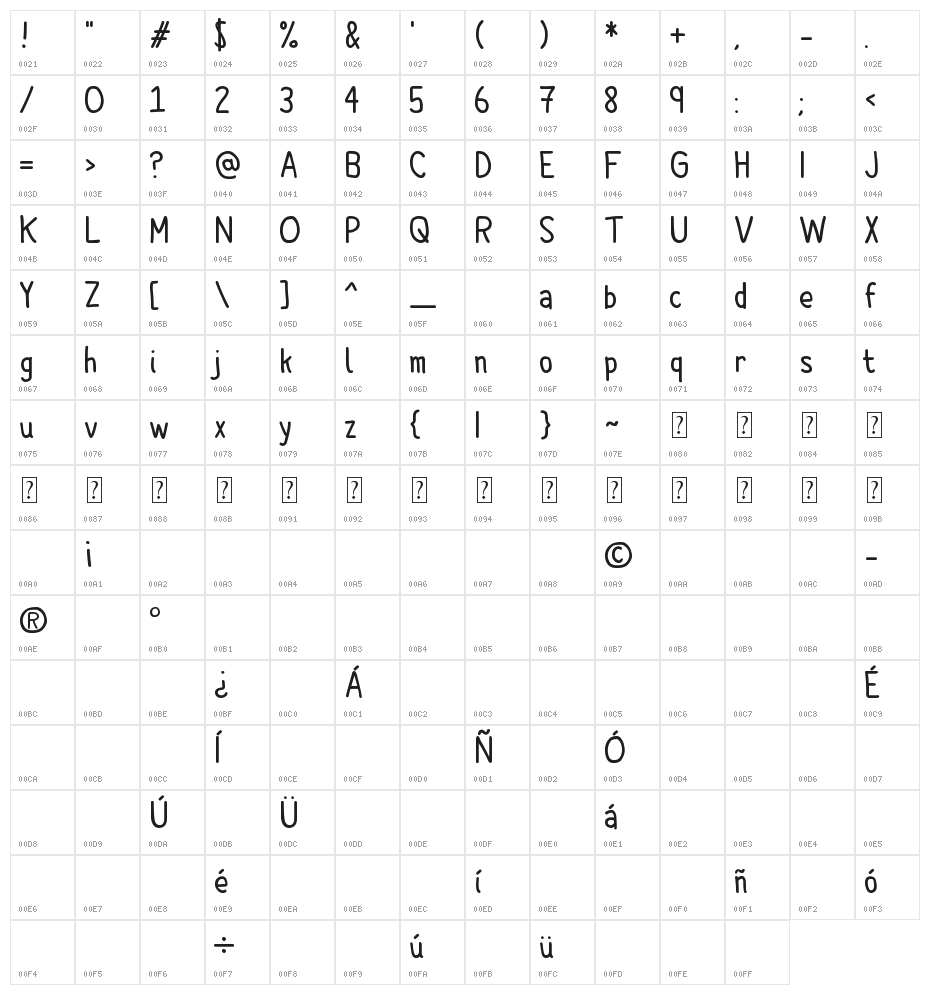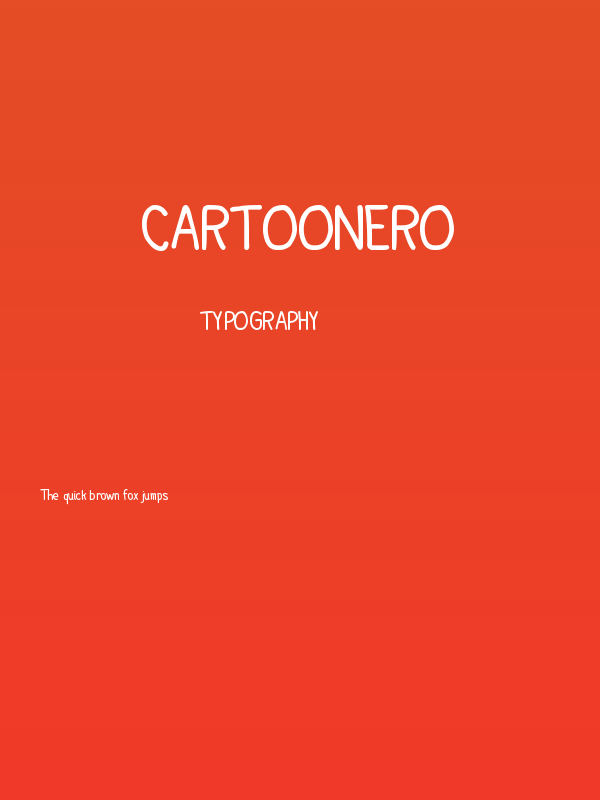
Cartoonero Font
Fonts by Omar Mogollón
| Anwendungsfall | Headlines, Logos, Informal Text |
| Vorgeschlagene Projekte | Ideal for children's books, comic strips, playful branding, and casual invitations. |